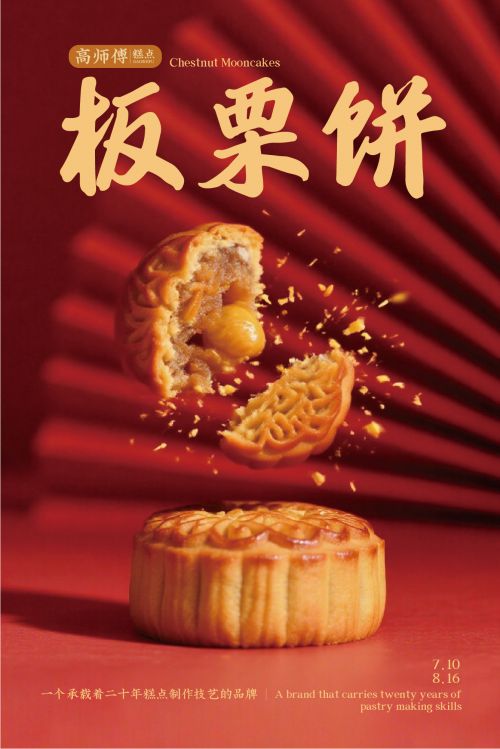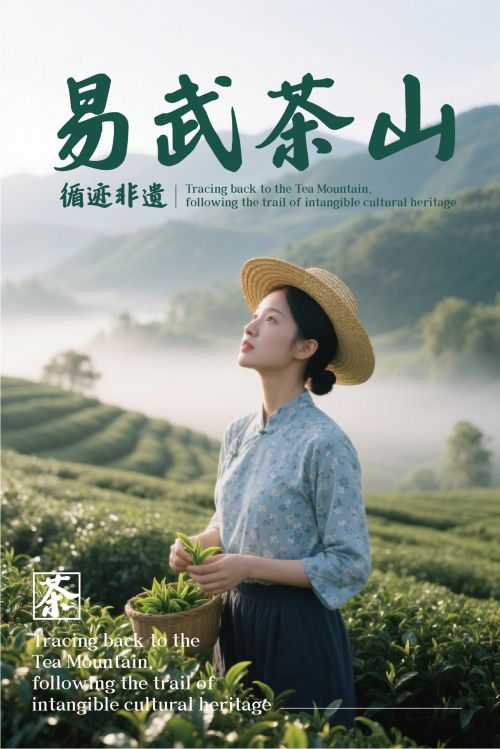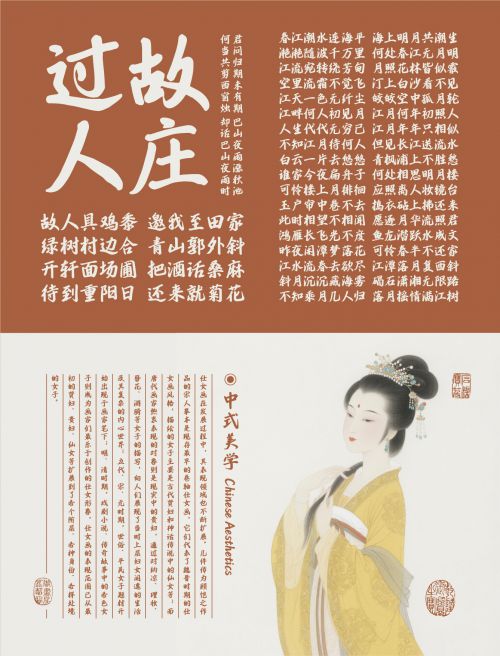
仓迹手写体
体以板写为基底,经细致打磨后,每一笔画都透着精修的质感。起笔收锋的弧度被反复校准,连笔处的过渡自然流畅,既保留了手写的温度,又添了份规整的精致。行楷的基因赋予它独特张力:楷书的端庄打底,行书的灵动加持,让字体在工整中藏着韵律感。用作标题时,既能镇住版面气场,又不因过于板正显得沉闷,恰是视觉焦点的理想选择。